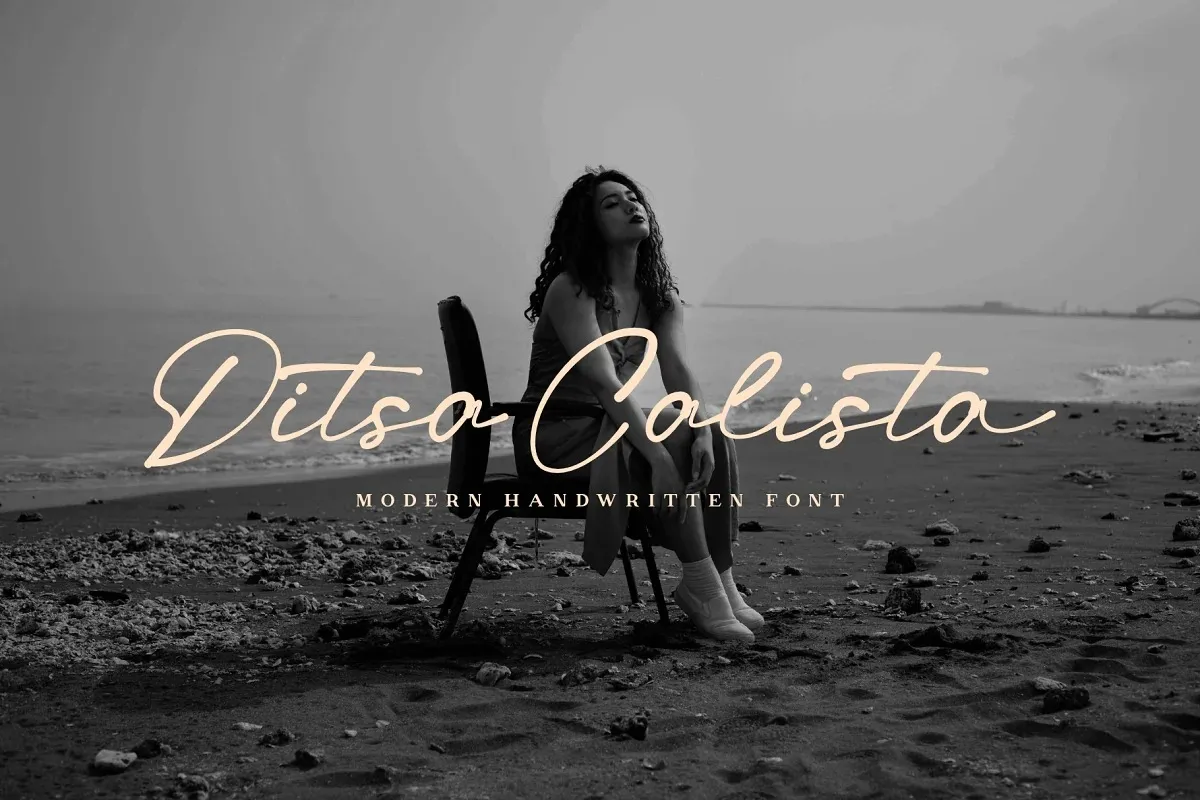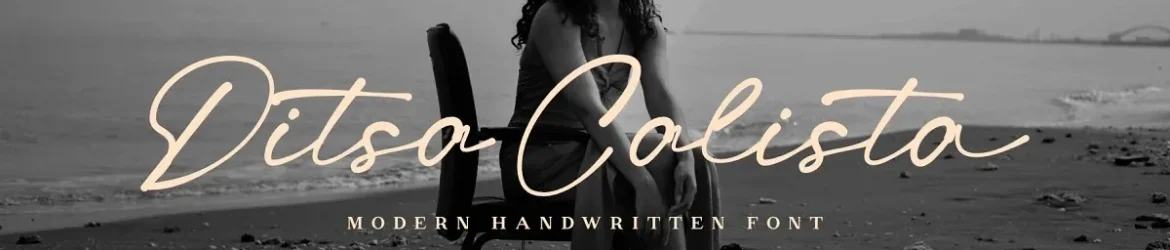
Ditsa Calista Font – Download Grátis
A Ditsa Calista Font é uma elegante escolha para designers buscando uma fonte script moderna e luxuosa. Seu estilo casual-chic contrasta perfeitamente com projetos de marca, cartões de visita e postagens do Instagram que você quer criar. Suas linhas fluidas e delicadas dão um toque sofisticado a qualquer projeto de design. É ideal para logos que precisam ser atraentes e memoráveis, e também serve bem para gráficos em redes sociais onde a simplicidade é crucial. A Ditsa Calista Font é uma escolha certeira se você busca uma fonte com um toque moderno e sofisticado, pronta para fazer sua marca brilhar na tela ou impressa.